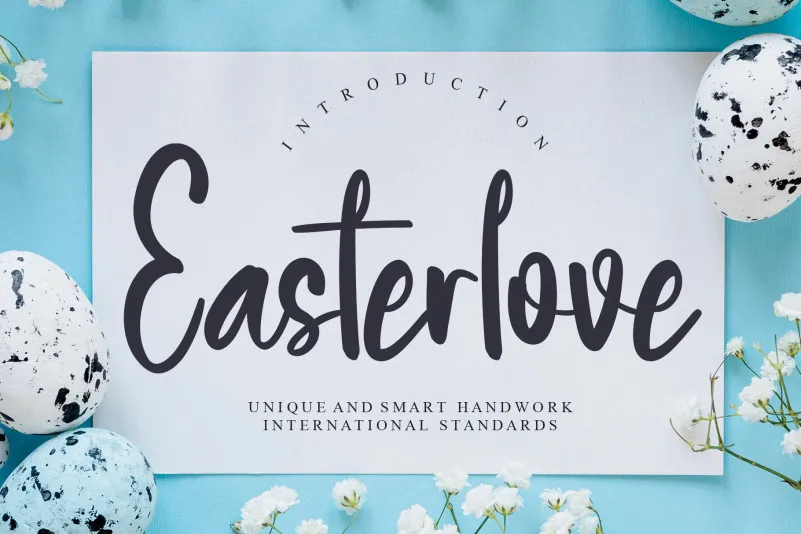
Easterlove Script Font – Download Grátis
A Easterlove Script Font oferece uma experiência única para designers e amantes do estilo handwritten. Inspirada no trabalho criativo dos designers da CreativeLetter, esta fonte é perfeita para aqueles que buscam algo autêntico e envolvente para seus projetos. Com suas linhas delicadas e traços fluidos, a Easterlove Script captura o encanto do estilo handwritten sem perder sua capacidade de expressar emoções intensas. Seja para criar cartões de aniversário personalizados ou adicionar um toque especial a qualquer projeto de escrita corporativa, esta fonte é uma escolha inteligente que irá destacar seu trabalho. Engajante e versátil, ela se adapta a todas as ocasiões e tornará sua marca mais única e memorável. Experimente agora e descubra por si mesmo o encanto desta fonte especial.